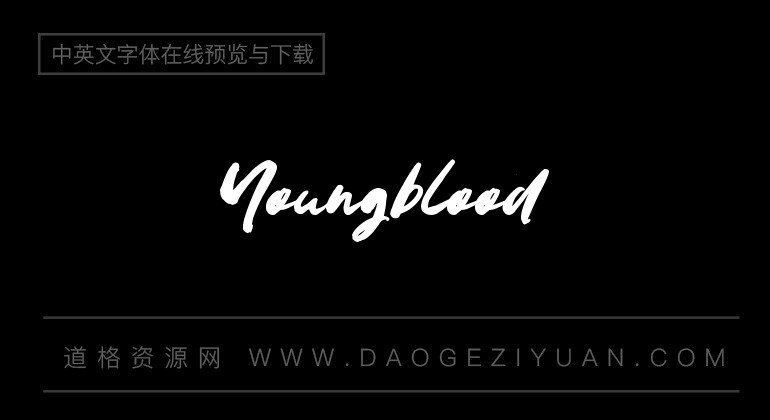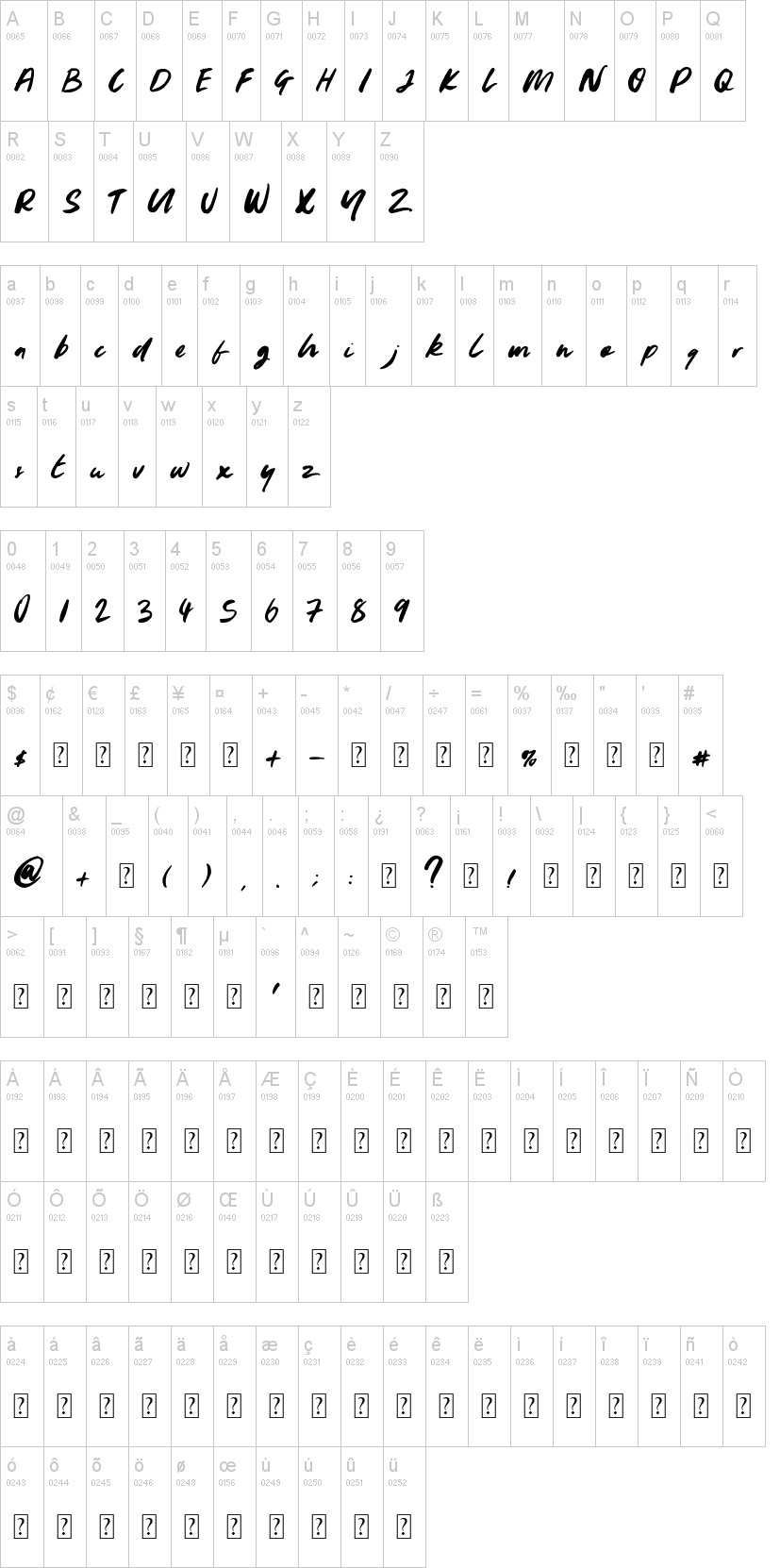
Youngblood
Youngblood是一种时尚的手写风格字体,由Matthew Smith设计。它拥有明亮的外观和强烈的个性,可用于各种场合,包括海报、标志、书籍封面等。它的设计灵感来自于手写字体,但在此基础上增加了一些独特的元素,使其看起来更加现代化。Youngblood字体的特点包括不规则的笔画和强烈的箭头形状,使它具有非常年轻和时尚的感觉。此外,Youngblood字体包括多种版本和风格,可根据需要进行选择,例如粗体、斜体等。
Youngblood是一款非常不错的手写艺术字体,具有很好的视觉感,适合于文化类的宣传设计、商业类品牌的广告和产品包装设计以及个性化文字排版等较多场景。